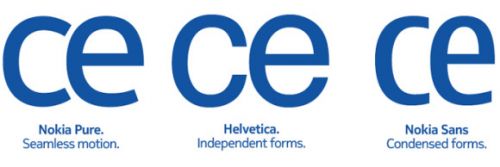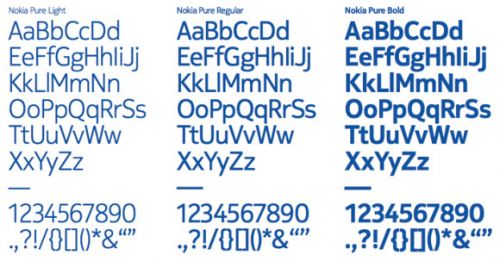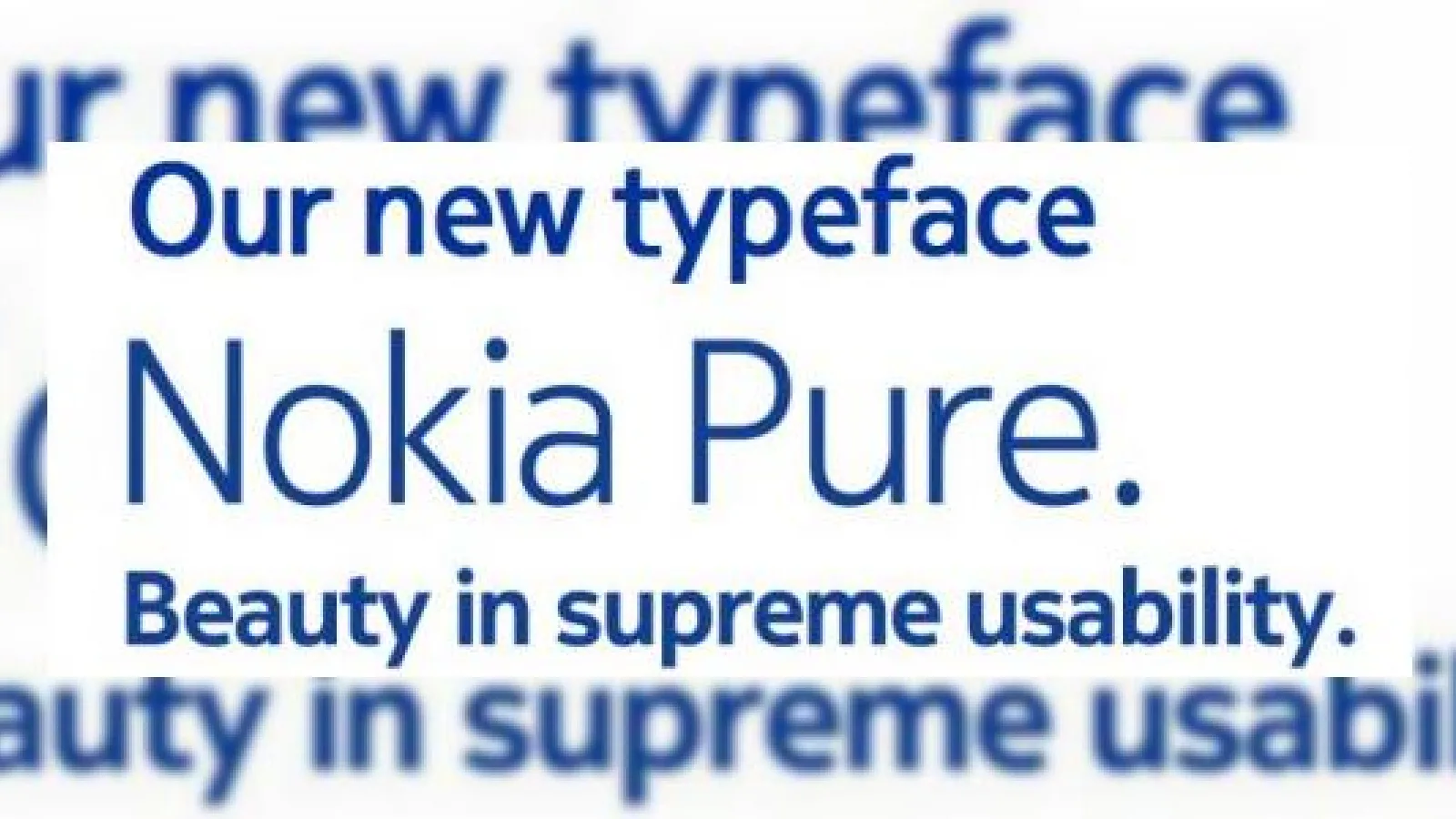
După ce și-a schimbat strategia pe piața telefoanelor, anunțând că se va axa pe Windows Phone 7 și mai puțin pe Symbian și MeeGo, Nokia trece la rebranduire. Primul pas făcut în această direcție este o schimbare de font, astfel că Nokia Sans este înlocuit cu Nokia Pure.
Deja fontul Nokia este unul dintre cele mai ușor de recunoscut din lume, dar finlandezii au simțit nevoia unui look modern. Era de ajuns să vedem un caracter sau două în culoare albastră pentru a ne da seama că acesta are legătură cu gigantul nord european. Ei bine, acum fontul adoptat este Nokia Pure, care va fi aplicat tuturor terminalelor Nokia, website-urilor companiei și documentelor oficiale.
Finlandezii afirmă că acest font a fost creat special pentru mediile digitale. Vom vedea oare o actualizare specială pentru Symbian^3 cu această ocazie?